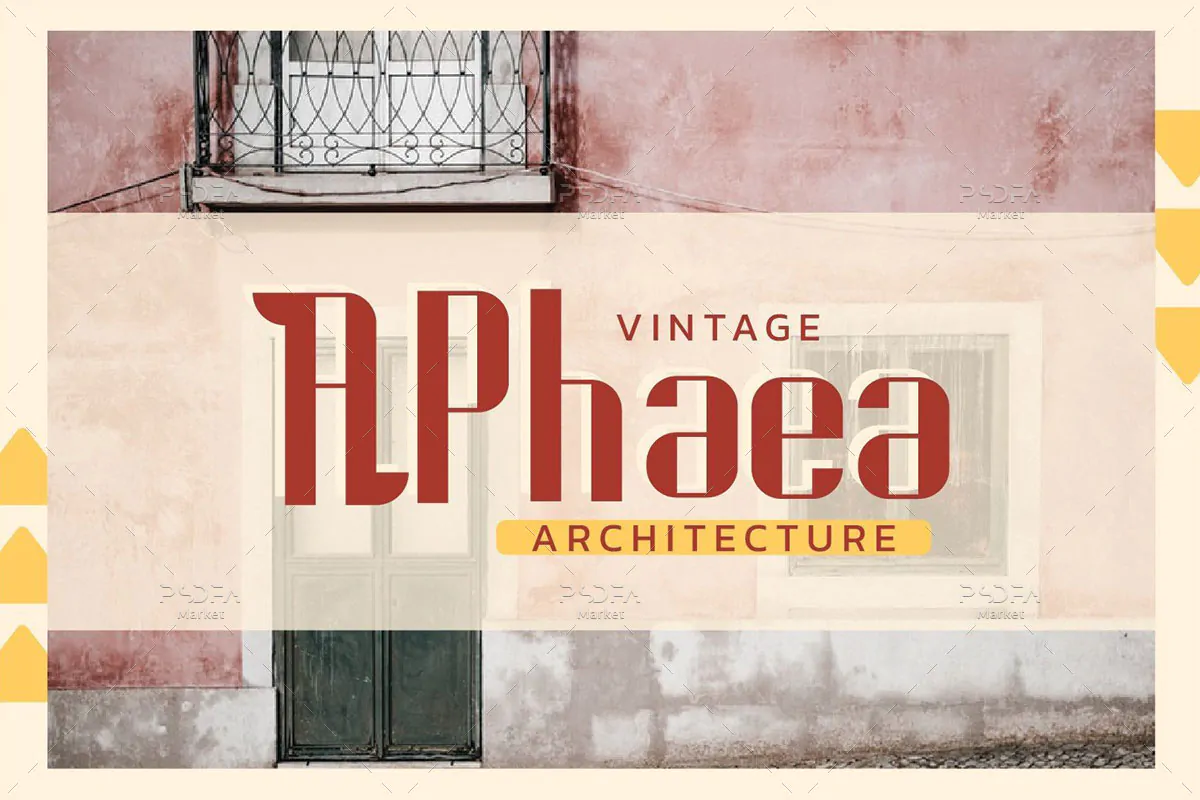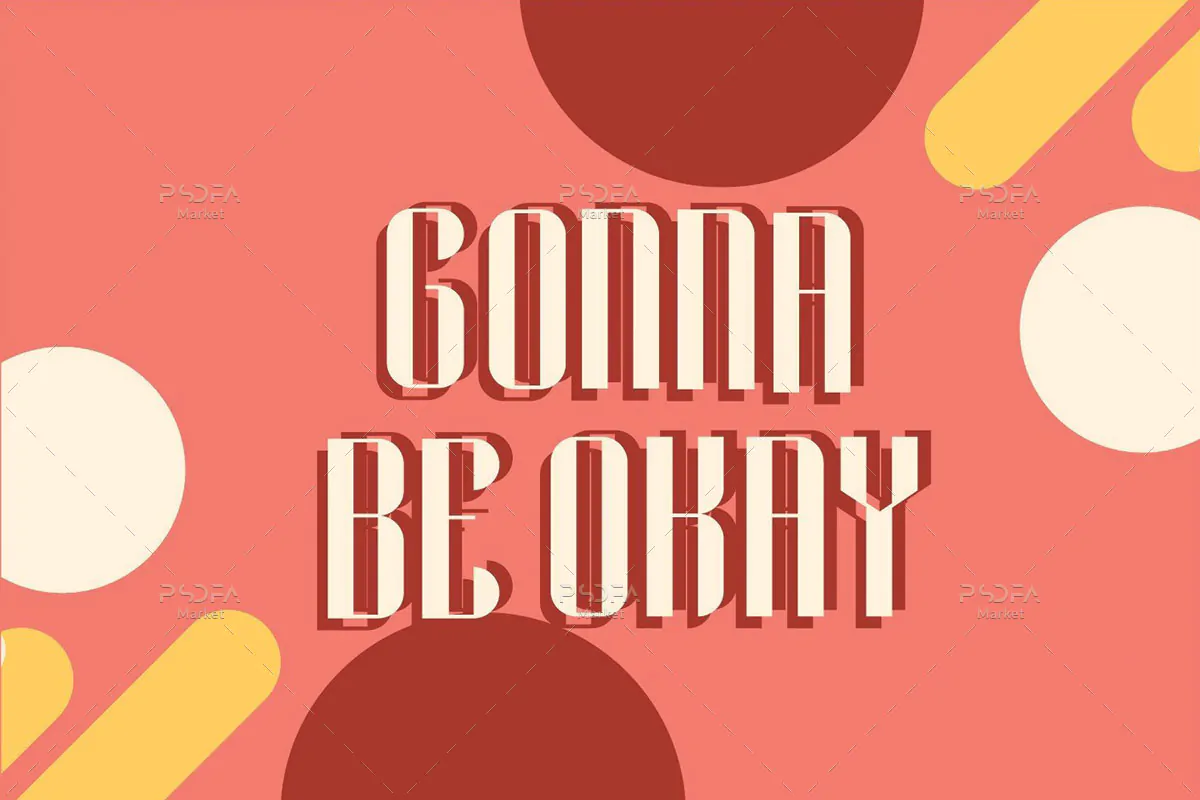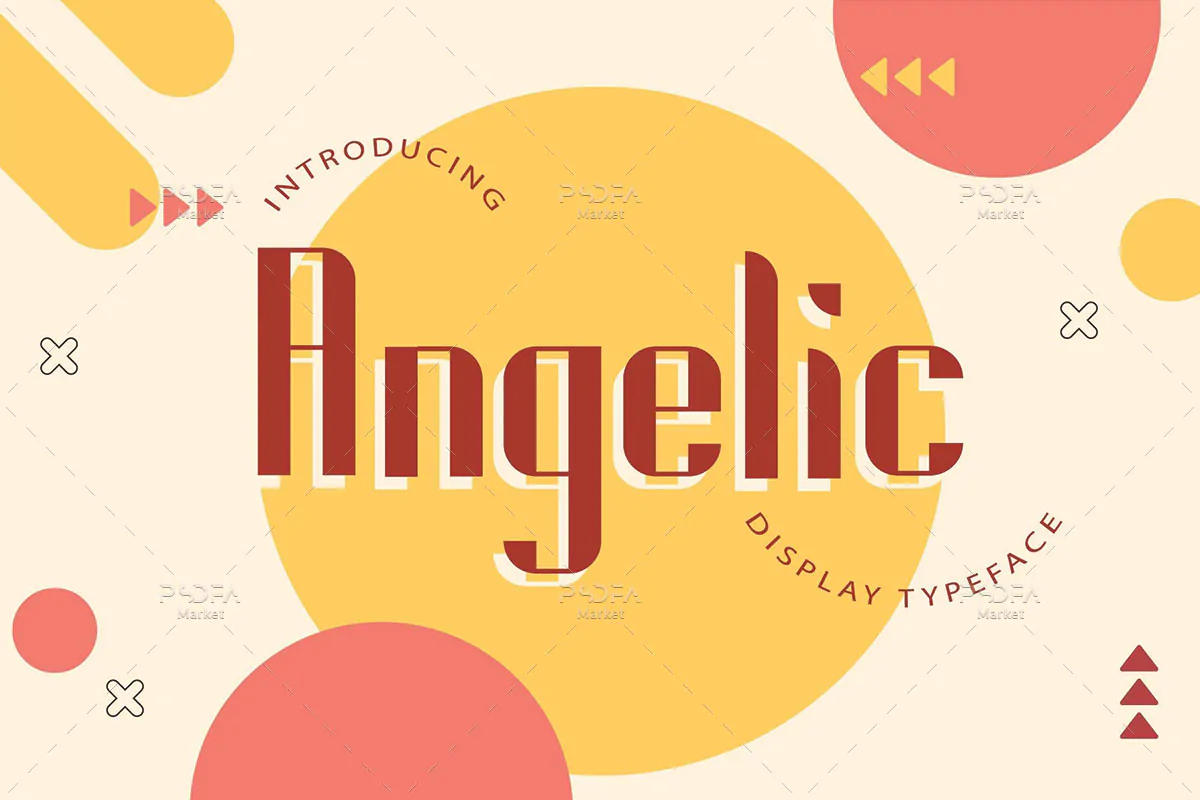
فونت نمایشی انگلیسی Angelic
فونت نمایشی انگلیسی
فونت نمایشی انگلیسی Angelic یک قلم زیبا با سبکی جالب است که مناسب جهت استفاده در طرح و پروژههای گرافیکی مختلف میباشد. فونت Angelic با وزن معمولی طراحی شده است که میتوانید از آن در طراحی انواع پوستر، بروشور، کارت ویزیت، کاور آلبوم موسیقی، بسته بندی محصولات و … استفاده کنید.